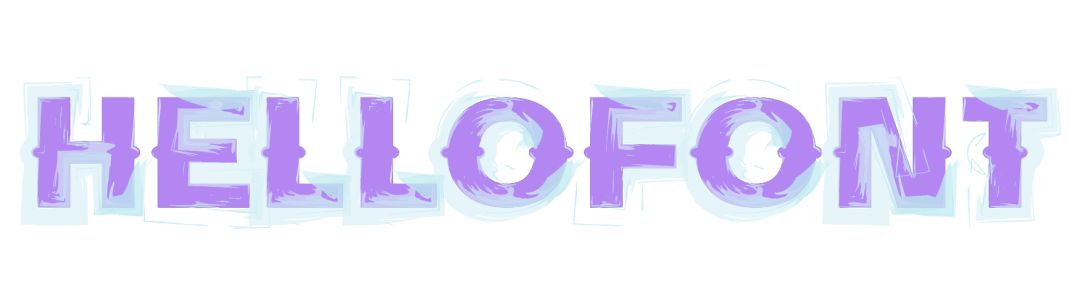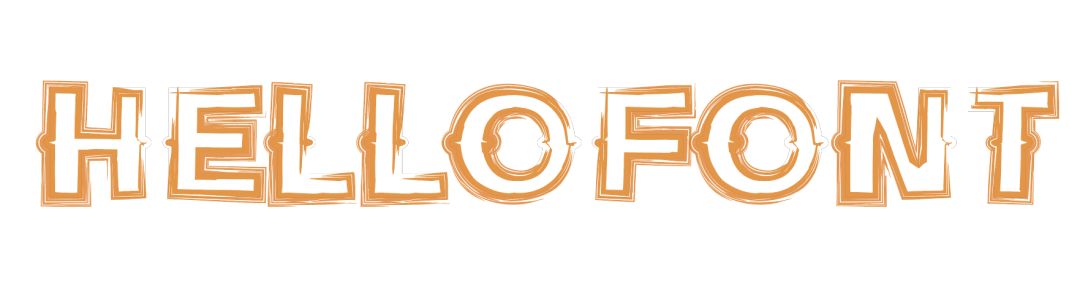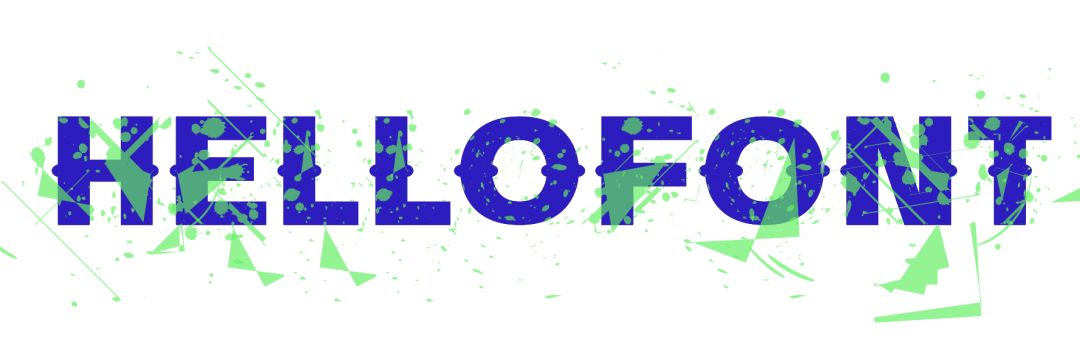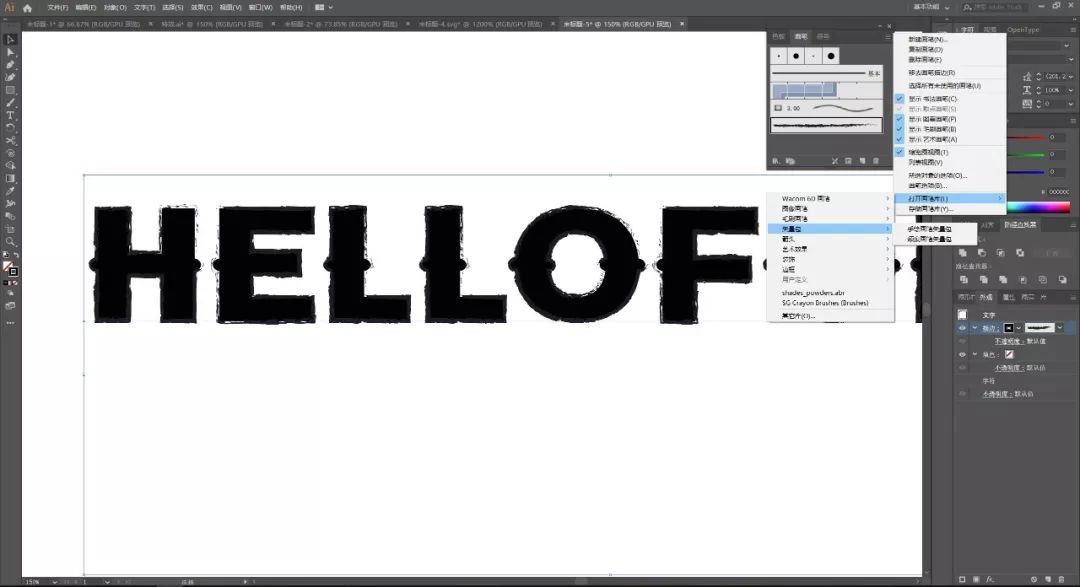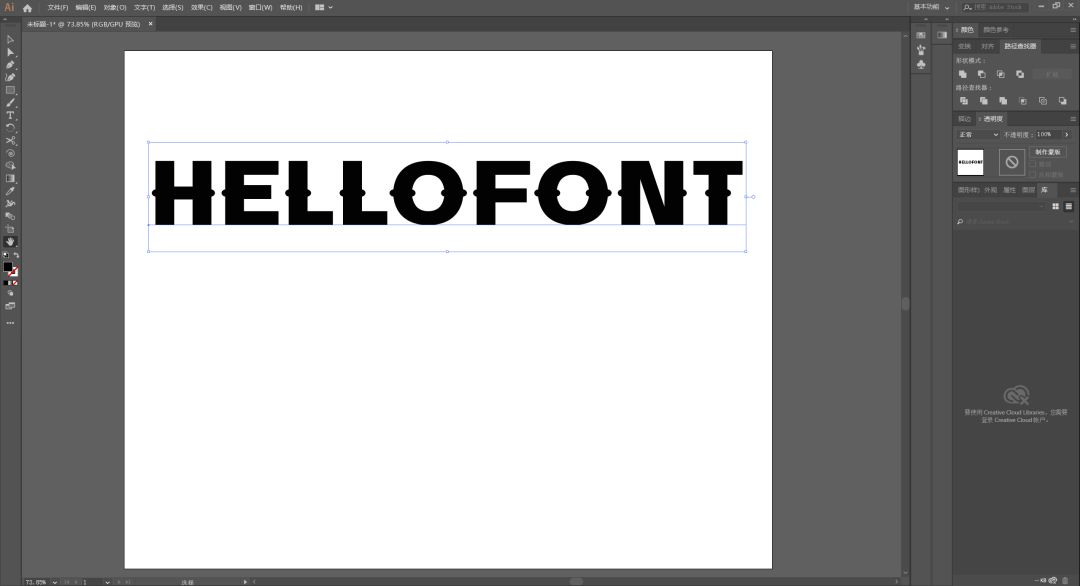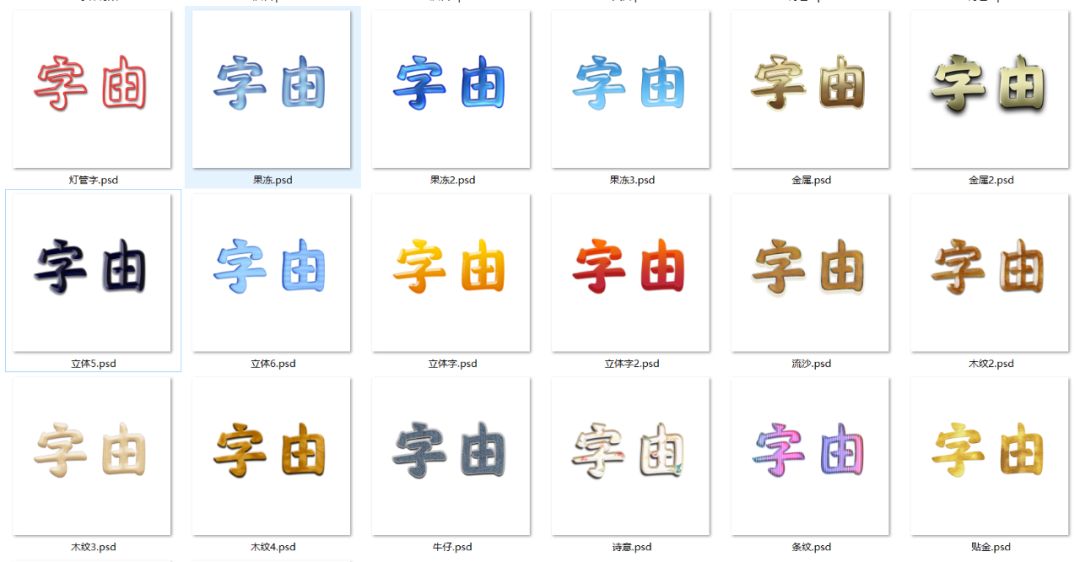
有了这套偷懒大法,特效字我没在怕的!
都知道字由上会员以后,有一些特效功能,省去了我们做字的时间(后续还会更新哦)~
但ps、ai也有这种一键式偷懒大法,你注意到了吗?
先来说ps,之前也发过资料(问卷调查),样式还记得吗?
它就相当于一个包装,让你的字体呈现出不同的质感。
只要打上文字,用字由客户端变换阿里汉仪智能黑体,再点击你喜欢的样式就可以了~
可以在效果中看到具体的参数,顺便学习下~
so easy吧,那如果是ai,又该如何呢?
当然是画笔,完全可以化妆式改变,这里用的字体是Bertha~
点击外观面板,添加新描边,接着就可以窗口>画笔了,ai自带的就有,打开画笔库。
下面都是我变的一些,还可以吧?